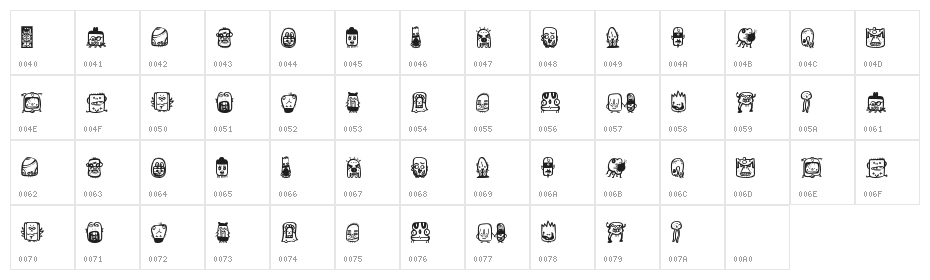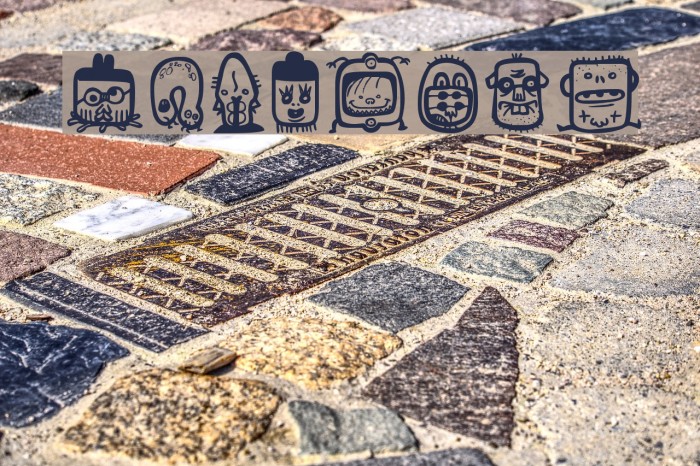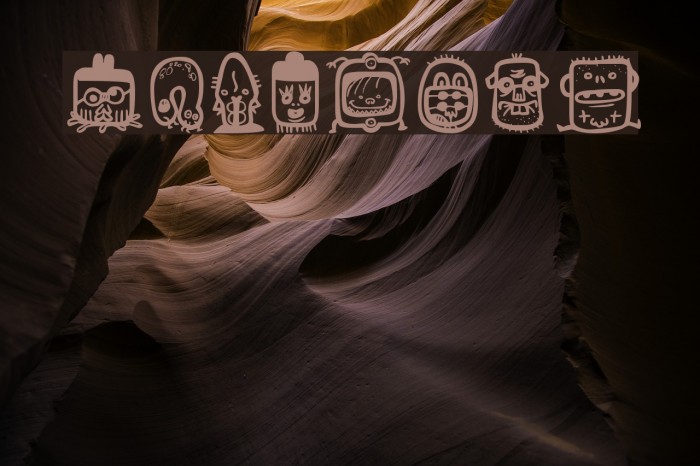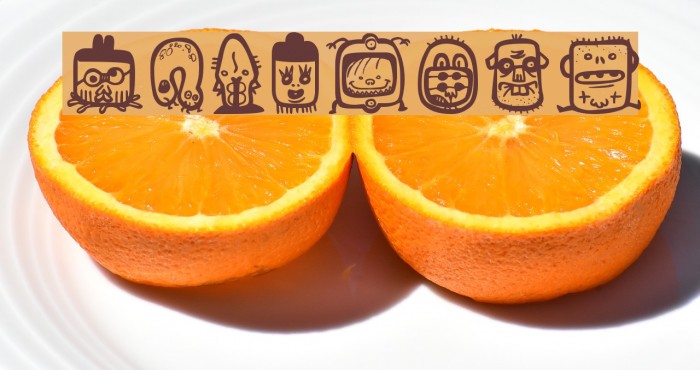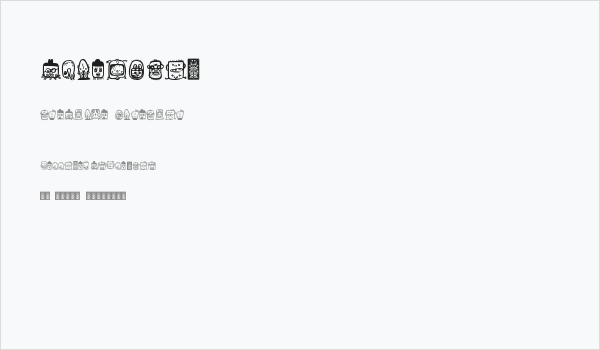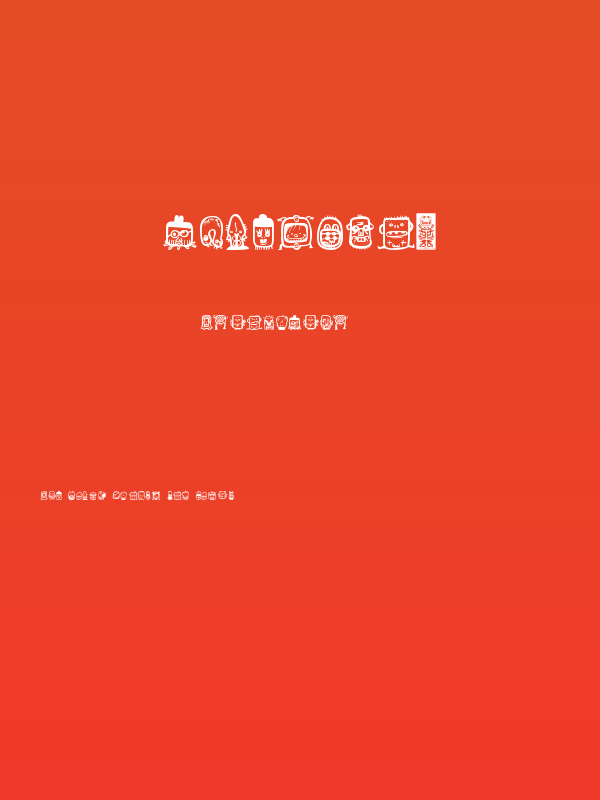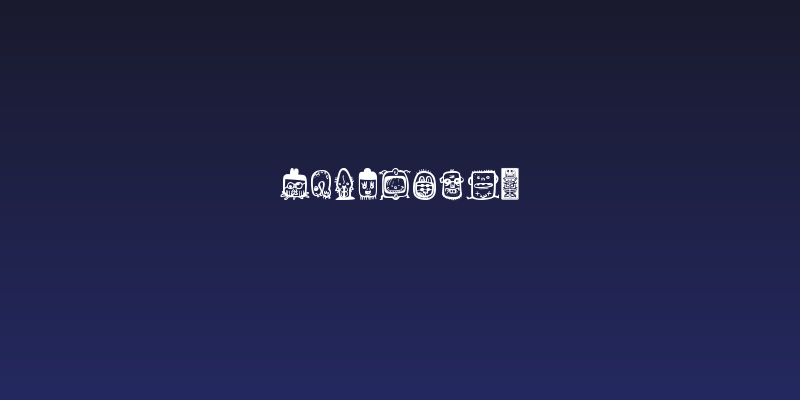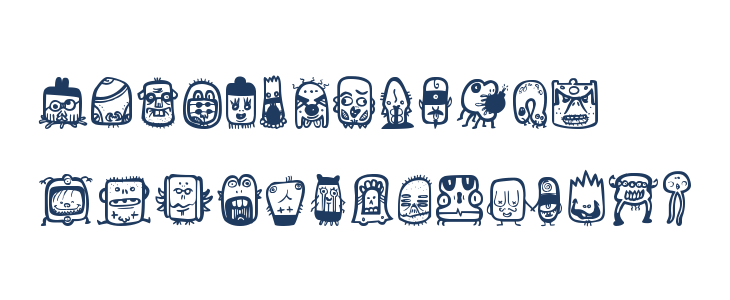
aliendco2 Font
✎ Dingbats
| Projetos propostos | Ideal for children's books, comic strips, playful branding, or any project needing a whimsical touch. |